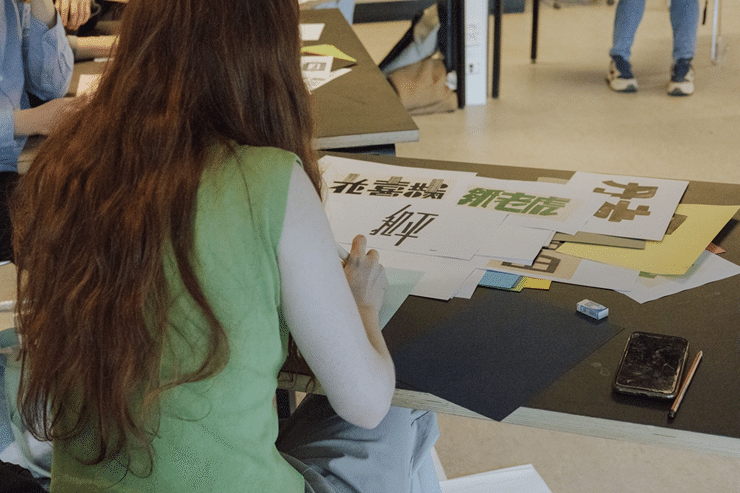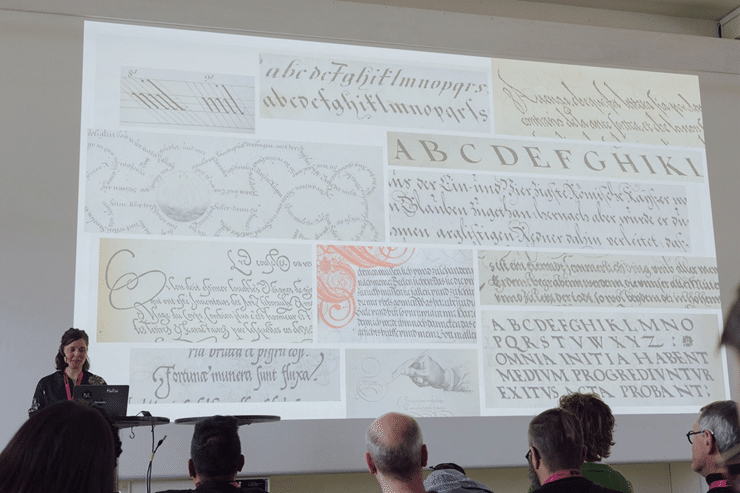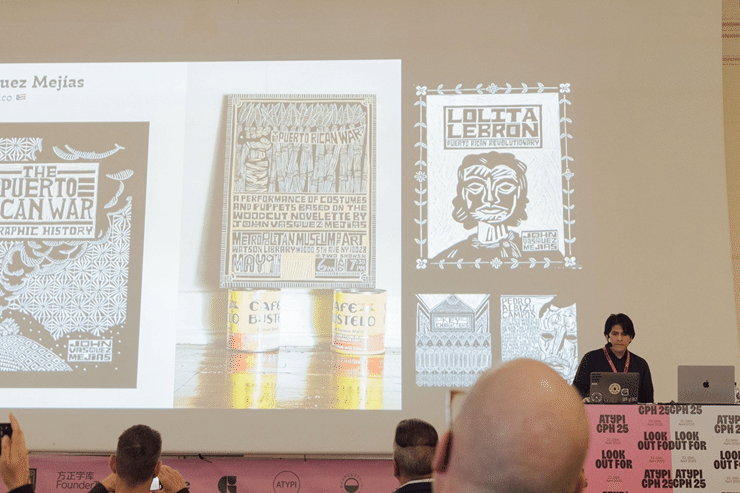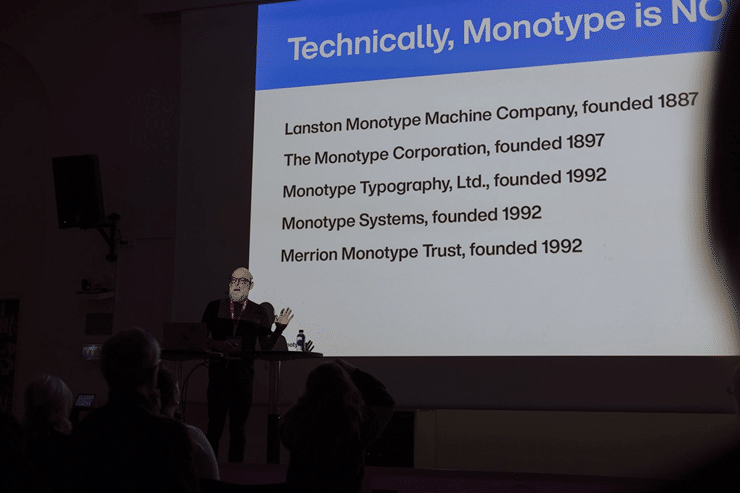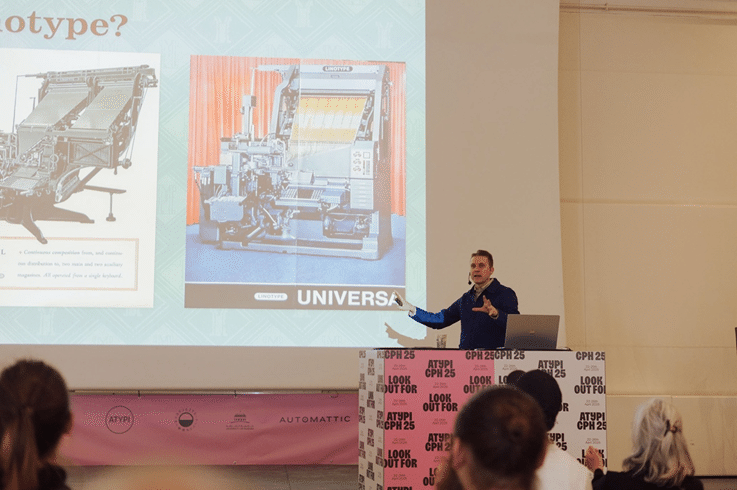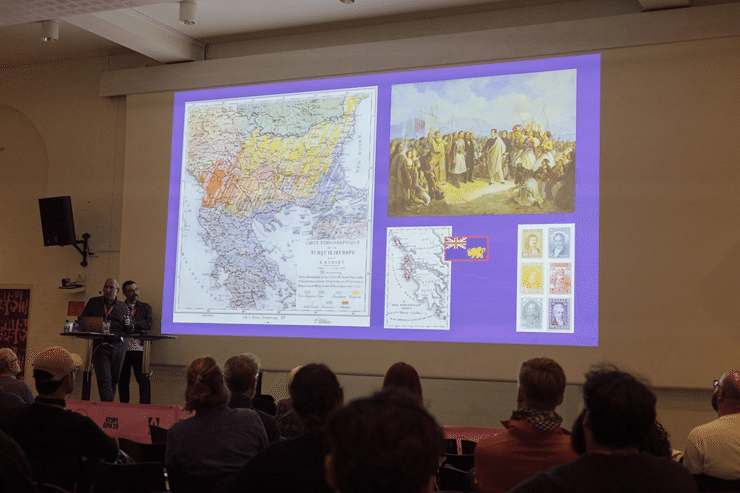
ATypI 2025 活动回顾:全球视角下的字体设计盛会
2025 年 4 月 22 日至 26 日,专注于字体排印与字体设计的国际会议 ATypI 在丹麦最大城市哥本哈根举行。
会议期间,两个会场共举办了 70 多场演讲,涵盖从活字字体、AI 驱动到可读性研究等多个主题。除了来自欧洲周边国家的与会者,也有不少亚洲地区的设计师参与。
来自蒙纳共 7 位成员登台发表演讲。其中,蒙纳亚太的两位字体设计师陶帝和土井辽太,聚焦于汉字设计,围绕 CCJK 字体(简体中文、繁体中文、日文、韩文)的设计,分享了实用技巧。
非母语设计的挑战与突破
左起:土井辽太、Jade Devaud、陶帝。
此次陶帝、土井辽太以及去年在日本办公室实习的法国学生 Jade Devaud 共同带来的演讲题为《提升 CCJK 字体设计:赋能全球设计师打造并识别高质量字体》。
近年来,越来越多的国内外企业需要应对 CCJK 语言,如何高效且高质量地制作字体,成为一项重要课题。无论是在设计非母语字体时选择外包,还是由公司内部的母语设计师负责,目前普遍存在的问题是:缺乏一种机制,可以让非母语设计师或团队,也能对这些字体进行有效评估。
因此,他们介绍了欧洲设计师学习日文字体设计,并参与实际项目的过程与成果。演讲内容围绕 CCJK 字体设计中的要点展开,并让讲解对于非母语设计师来说也易于理解。
土井辽太:
今年 2 月我与陶帝曾在曼谷举行的 BITS Conference 上也发表过类似内容的演讲,而这次则特别邀请了 Jade 参与,将她作为实习生的真实经历分享给现场观众。
陶帝:
演讲结束后,我们收到了许多观众非常积极的反馈。大家对 Jade 出色的工作表现和她作为一位专业人士的成长感到非常钦佩。许多听众表示,这种连接亚洲与西方视角的跨文化合作,正是未来字体设计行业创新与发展的关键动力。
Jade:
直到会议最后一天,仍有不少人与我们交流,并对我们的演讲表达感谢。大家特别提到,我们将一个较为复杂的主题讲解得通俗易懂,这让我印象深刻。此外,有很多人表示,他们不仅在职业层面上,对 CCJK 字体设计及日本书法产生了浓厚兴趣,甚至也将其视为个人爱好。这次能被从初学者到专业设计师的广泛听众接受,我感到非常开心与感激。
更多分享:跨文化视角与行业前瞻
这次 ATypI 大会上,还有另外 5 位蒙纳成员登台发表了演讲。
字体工程师 Petra Rüth 分享了她关于“反斜体(backslant)”的研究成果。所谓反斜体,是相对于意大利斜体方向相反的字体形式。她从 16 世纪的铜版印刷与书法实践出发,细致考察了反斜体文字的起源与演变过程,为大家带来了一场极具深度的历史回顾与字体研究讲解。
高级字体设计师 Juan Villanueva 则带来了一场充满力量的演讲,表达了他对拉丁美洲文化的认同与责任感。他深入探讨了字体设计、社会影响与文化传承之间的交汇点,其真挚而富有使命感的分享,给在场的许多听众留下了深刻印象。
字库产品管理总监 Dan Rhatigan 则围绕蒙纳的定位,以及如何应对不断变化的市场需求进行了分享。他结合数据与市场分析,详细介绍了公司为客户及合作字库提供的支持服务,并展望了字体行业未来的发展潜力,内容专业且富有前瞻性。
创意服务总监 Doug Wilson 分享了一个颇具历史意味的故事:由德国移民发明的莱诺排字机(Linotype)如何被“逆向进口”回德国,却一度遭遇当地印刷业的质疑。他讲述了 Linotype 从成立、经历两次世界大战,到如今仍在进行的 Linotype Book Project 的历程,为听众带来了一段跨越技术与时代的字体史回顾。
最后,字体创意总监 Emilios Theofanous 与在英国研究生院教授字体设计的 Gerry Leonidas 共同发表了关于希腊文字体排印面临的诸多挑战的演讲。
他们指出了 Unicode 编码不一致、字符点缺失、键盘输入支持不足等技术问题,并进一步探讨了这些问题对年轻一代使用习惯的影响,以及目前字体业界正展开的跨领域协作努力,致力于改善这一现状。
总结:立足本土,沟通全球
除了演讲之外,ATypI 还举办了工作坊等活动,土井辽太表示,在工作坊中既体验了使用专用软件制作字体,也通过传统手工方法亲身设计,并通过Matthias Horneman-Thielcke 先生的带领深入了解了丹麦字体设计的历史,看到了很多平时难得一见的档案资料。
这次大会带来了许多启发性的体验。亲眼见证亚洲与西方字体设计行业各自走过的不同道路,也促使大家产生了更多灵感。作为扎根亚洲的设计师,能够再次感受到这片区域的字体设计领域仍蕴藏巨大潜力。